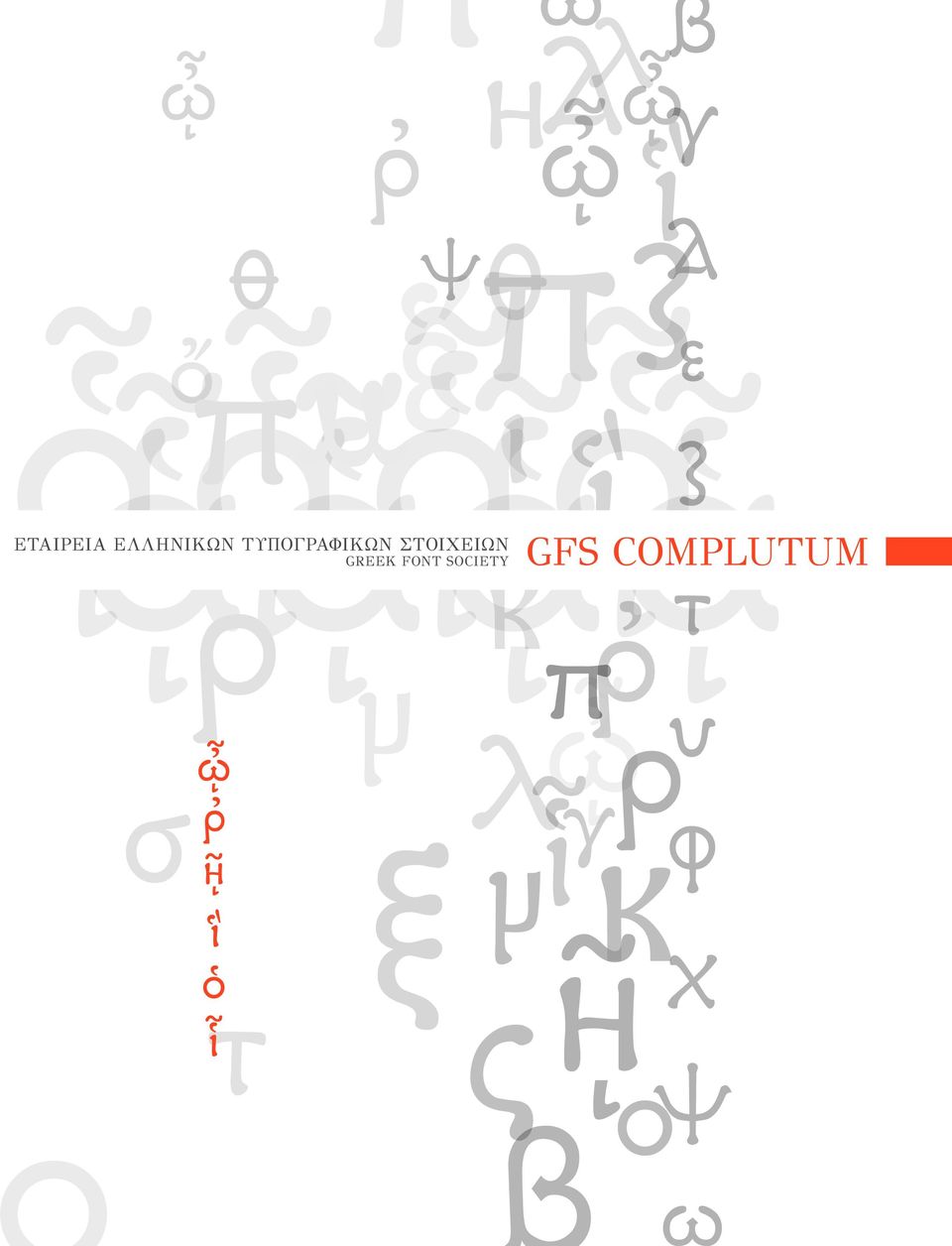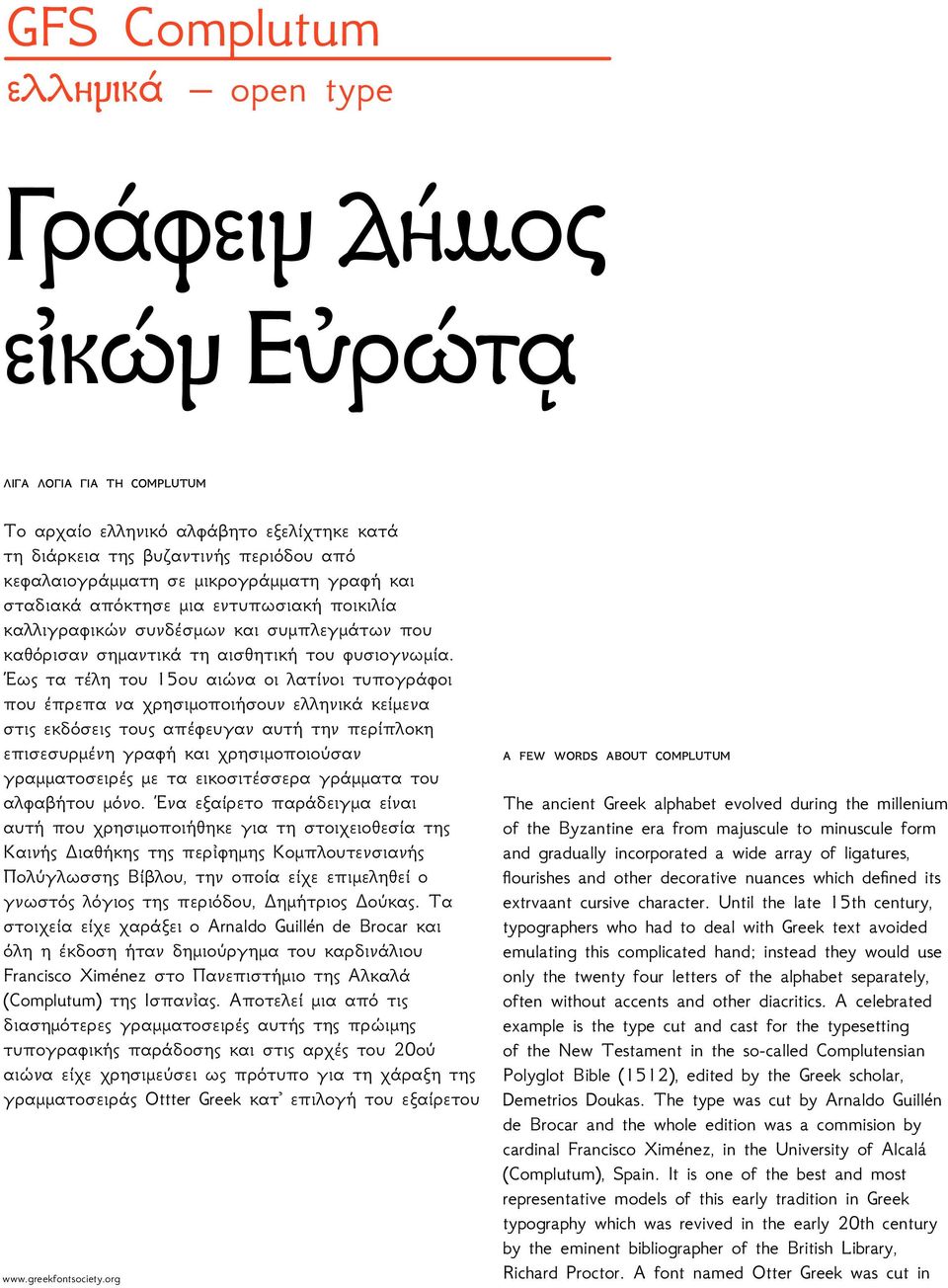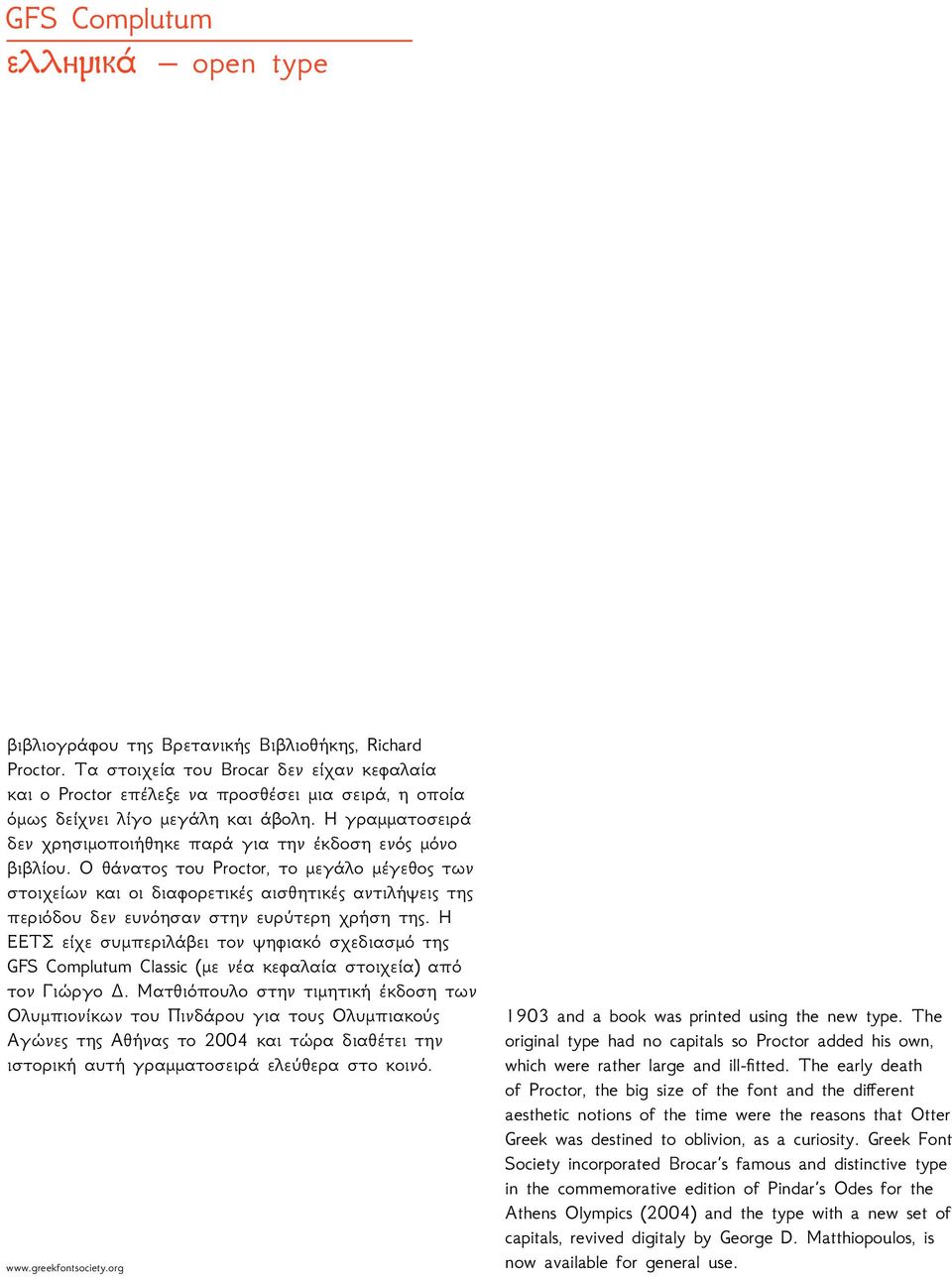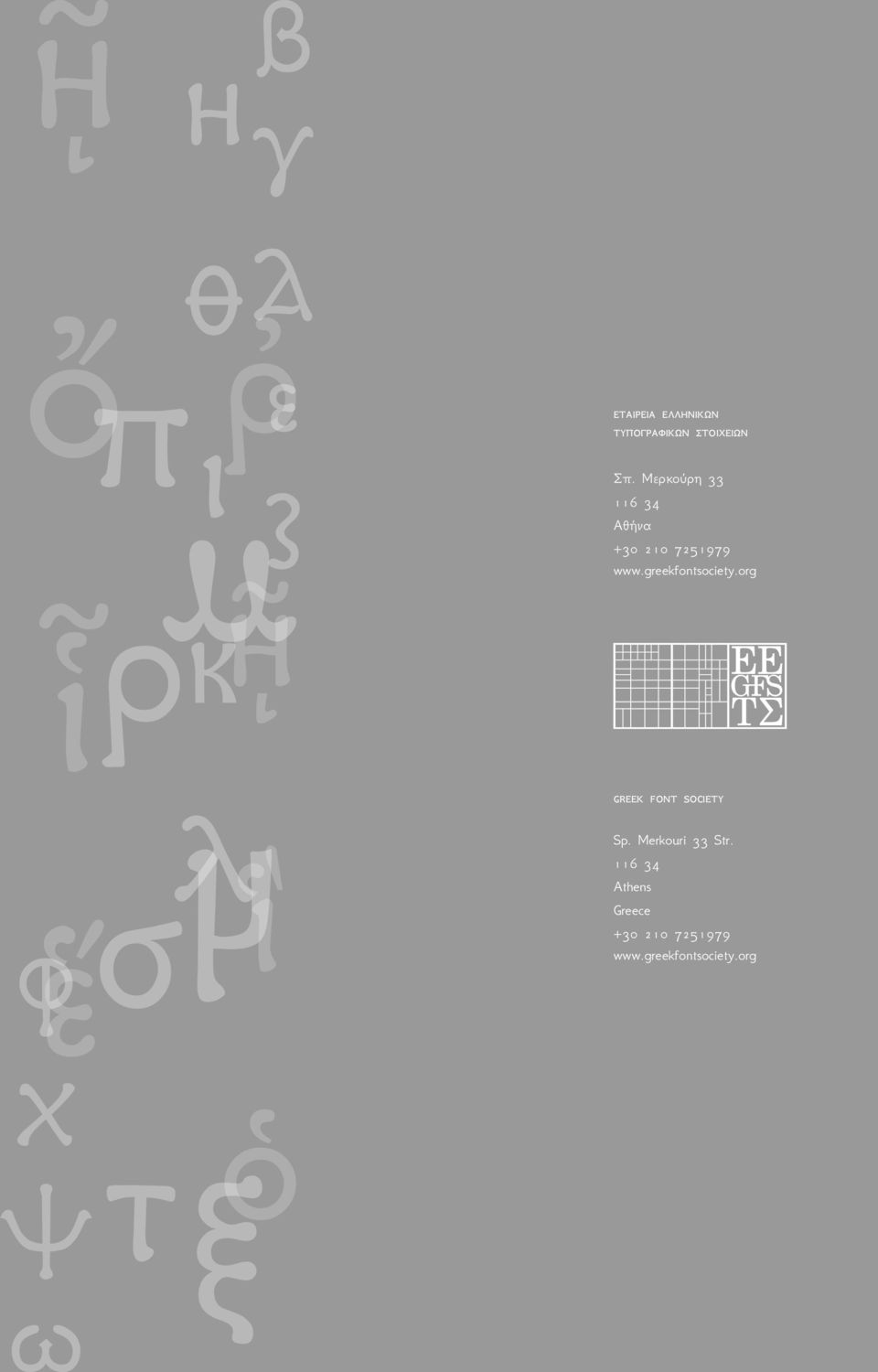
ΕΤΑΙΡΕΙΑ ΕΛΛΗΝΙΚΩΝ ΤΥΠΟΓΡΑΦΙΚΩΝ ΣΤΟΙΧΕΙΩΝ GREEK FONT SOCIETY GFS COMPLUTUM
1 ΕΤΑΙΡΕΙΑ ΕΛΛΗΝΙΚΩΝ ΤΥΠΟΓΡΑΦΙΚΩΝ ΣΤΟΙΧΕΙΩΝ GREEK FONT SOCIETY GFS COMPLUTUM
2 ελληνικά open type Γράφειν δήμος εἰκών Εὐρώτᾳ ΛΊΓΆ ΛΌΓΊΆ ΓΊΆ ΤΉ COMPLUTUM Το αρχαίο ελληνικό αλφάβητο εξελίχτηκε κατά τη διάρκεια της βυζαντινής περιόδου από κεφαλαιογράμματη σε μικρογράμματη γραφή και σταδιακά απόκτησε μια εντυπωσιακή ποικιλία καλλιγραφικών συνδέσμων και συμπλεγμάτων που καθόρισαν σημαντικά τη αισθητική του φυσιογνωμία. Έως τα τέλη του 15ου αιώνα οι λατίνοι τυπογράφοι που έπρεπα να χρησιμοποιήσουν ελληνικά κείμενα στις εκδόσεις τους απέφευγαν αυτή την περίπλοκη επισεσυρμένη γραφή και χρησιμοποιούσαν γραμματοσειρές με τα εικοσιτέσσερα γράμματα του αλφαβήτου μόνο. Ένα εξαίρετο παράδειγμα είναι αυτή που χρησιμοποιήθηκε για τη στοιχειοθεσία της Καινής Διαθήκης της περἰφημης Κομπλουτενσιανής Πολύγλωσσης Βίβλου, την οποία είχε επιμεληθεί ο γνωστός λόγιος της περιόδου, Δημήτριος Δούκας. Τα στοιχεία είχε χαράξει ο Arnaldo Guillén de Brocar και όλη η έκδοση ήταν δημιούργημα του καρδινάλιου Francisco Ximénez στο Πανεπιστήμιο της Αλκαλά (Complutum) της Ισπανἰας. Αποτελεί μια από τις διασημότερες γραμματοσειρές αυτής της πρώιμης τυπογραφικής παράδοσης και στις αρχές του 20ού αιώνα είχε χρησιμεύσει ως πρότυπο για τη χάραξη της γραμματοσειράς Ottter Greek κατ επιλογή του εξαίρετου A FEW WORDS ABOUT COMPLUTUM The ancient Greek alphabet evolved during the millenium of the Byzantine era from majuscule to minuscule form and gradually incorporated a wide array of ligatures, flourishes and other decorative nuances which defined its extrvaant cursive character. Until the late 15th century, typographers who had to deal with Greek text avoided emulating this complicated hand; instead they would use only the twenty four letters of the alphabet separately, often without accents and other diacritics. A celebrated example is the type cut and cast for the typesetting of the New Testament in the so-called Complutensian Polyglot Bible (1512), edited by the Greek scholar, Demetrios Doukas. The type was cut by Arnaldo Guillén de Brocar and the whole edition was a commision by cardinal Francisco Ximénez, in the University of Alcalá (Complutum), Spain. It is one of the best and most representative models of this early tradition in Greek typography which was revived in the early 20th century by the eminent bibliographer of the British Library, Richard Proctor. A font named Otter Greek was cut in
3 ελληνικά open type βιβλιογράφου της Βρετανικής Βιβλιοθήκης, Richard Proctor. Τα στοιχεία του Brocar δεν είχαν κεφαλαία και ο Proctor επέλεξε να προσθέσει μια σειρά, η οποία όμως δείχνει λίγο μεγάλη και άβολη. Η γραμματοσειρά δεν χρησιμοποιήθηκε παρά για την έκδοση ενός μόνο βιβλίου. Ο θάνατος του Proctor, το μεγάλο μέγεθος των στοιχείων και οι διαφορετικές αισθητικές αντιλήψεις της περιόδου δεν ευνόησαν στην ευρύτερη χρήση της. Η ΕΕΤΣ είχε συμπεριλάβει τον ψηφιακό σχεδιασμό της GFS Complutum Classic (με νέα κεφαλαία στοιχεία) από τον Γιώργο Δ. Ματθιόπουλο στην τιμητική έκδοση των Ολυμπιονίκων του Πινδάρου για τους Ολυμπιακούς Αγώνες της Αθήνας το 2004 και τώρα διαθέτει την ιστορική αυτή γραμματοσειρά ελεύθερα στο κοινό and a book was printed using the new type. The original type had no capitals so Proctor added his own, which were rather large and ill-fitted. The early death of Proctor, the big size of the font and the different aesthetic notions of the time were the reasons that Otter Greek was destined to oblivion, as a curiosity. Greek Font Society incorporated Brocar s famous and distinctive type in the commemorative edition of Pindar s Odes for the Athens Olympics (2004) and the type with a new set of capitals, revived digitaly by George D. Matthiopoulos, is now available for general use.
4 πόλύτόνίκό POLYTONIC πόλύτόνίκό ΣΎΝΌΛΌ ΧΆρΆΚΤΉρΏΝ ΑΒΓ ΕΖΗΘΙΚΛΜΝΞΟΠΡΣΤΥΦΧΨΩ ΆΈΉΊΪΌΎ ΫΏ ΆἉἍἋἏᾸᾺᾼᾉᾍᾋ ᾏᾈᾌᾊᾎ ἈἌἊἎᾹ ΈἙἝἛῈἘἜἚ ΉἩἭἫἯῊῌᾙᾝᾛᾟᾘᾜ ᾚᾞἨἬἪἮ ΊἹἽἻἿῘῚἸἼἺἾῙ ΌὉὍὋῸὈὌὊῬ ΎὙὝὛὟῨῪῩ ΏὩὭὫὯῺῼᾩᾭᾫᾯᾨᾬ ᾪᾮὨὬὪὮ αβγδεζηθικλμνξοπρστυφχψως άέήίϊ ΐόύΰϋώ ὰάἀἁἂἃἄἅἆἇᾀᾁᾂᾃᾄᾅᾆᾇᾰᾱᾲᾳᾴᾶᾷ ὲέἐἑἒ ἓ ἔἕ ὴήᾐᾑᾒᾓᾔᾕᾖᾗῂῃῄῆῇἠἡἢἣἤἥἦἧ ὶί ῐ ῑ ῒ ΐ ῖ ῗἰἱ ἲ ἳ ἴ ἵ ἶἷ ὸόὀὁὂὃὄὅῤῥ ὺύὐὑὒὓὔὕὖὗῠῡῢΰῦῧ ὼώὠὡὢὣὤὥὦὧᾠᾡᾢᾣᾤᾥᾦᾧῲῳῴῶῷ
5 SAMPLE TEXTS COMPLUTUM ΛΈΎΚΆ 6 ΣΤΊΓµΈΣ Η ΣΥΝΑΝΤΗΣΗ των πνευματικών και καλλιτεχνικών παραδόσεων της Ελληνικής Ανατολής και της ευρωπαϊκής Δύσης στην Κρήτη την εποχή της Βενετοκρατίας οδήγησε σε διάφορες ζυμώσεις και δημιούργησε το κατάλληλο κλίμα για την ανάπτυξη και καρποφορία στο νησί ενός πολιτισμού με πολλές εκφάνσεις και ιδιαίτερες αποχρώσεις. Στην τελευταία ιδίως περίοδο της Βενετοκρατίας στην οικονομική ευημερία των κρητικών πόλεων της πρωτεύουσας. COMPLUTUM ΛΈΎΚΆ 7 ΣΤΊΓµΈΣ Η ΣΥΝΑΝΤΗΣΗ των πνευματικών και καλλιτεχνικών παραδόσεων της Ελληνικής Ανατολής και της ευρωπαϊκής Δύσης στην Κρήτη την εποχή της Βενετοκρατίας οδήγησε σε διάφορες ζυμώσεις και δημιούργησε το κατάλληλο κλίμα για την ανάπτυξη και καρποφορία στο νησί ενός πολιτισμού με πολλές εκφάνσεις και ιδιαίτερες αποχρώσεις. COMPLUTUM ΛΈΎΚΆ 8 ΣΤΊΓµΈΣ Η ΣΥΝΑΝΤΗΣΗ των πνευματικών και καλλιτεχνικών παραδόσεων της Ελληνικής Ανατολής και της ευρωπαϊκής Δύσης στην Κρήτη την εποχή της Βενετοκρατίας οδήγησε σε διάφορες ζυμώσεις και δημιούργησε το κατάλληλο κλίμα για την ανάπτυξη και καρποφορία στο νησί ενός πολιτισμού με COMPLUTUM ΛΈΎΚΆ 9 ΣΤΊΓµΈΣ Η ΣΥΝΑΝΤΗΣΗ των πνευματικών και καλλιτεχνικών παραδόσεων της Ελληνικής Ανατολής και της ευρωπαϊκής Δύσης στην Κρήτη την εποχή της Βενετοκρατίας οδήγησε σε διάφορες ζυμώσεις και COMPLUTUM ΛΈΎΚΆ 10 ΣΤΊΓµΈΣ Η ΣΥΝΑΝΤΗΣΗ των πνευματικών και καλλιτεχνικών παραδόσεων της Ελληνικής Ανατολής και της ευρωπαϊκής Δύσης στην Κρήτη την εποχή της Βενετοκρατίας οδήγησε σε COMPLUTUM ΛΈΎΚΆ 12 ΣΤΊΓµΈΣ Η ΣΥΝΑΝΤΗΣΗ των πνευματικών και καλλιτεχνικών παραδόσεων της Ελληνικής Ανατολής COMPLUTUM ΛΈΎΚΆ 14 ΣΤΊΓµΈΣ Η ΣΥΝΑΝΤΗΣΗ των πνευματικών και καλλιτεχνικών παραδόσεων της Ελληνικής SAMPLE TEXT 12 PT GFS COMPLUTUM Η συνάντηση των πνευματικών και καλλιτεχνικών παραδόσεων της Ελληνικής Ανατολής και της ευρωπαϊκής Δύσης στην Κρήτη την εποχή της Βενετοκρατίας οδήγησε σε διάφορες ζυμώσεις και δημιούργησε το κατάλληλο κλίμα για την ανάπτυξη και καρποφορία στο νησί ενός πολιτισμού με πολλές εκφάνσεις και ιδιαίτερες αποχρώσεις. Στην τελευταία ιδίως περίοδο της Βενετοκρατίας στην οικονομική ευημερία των κρητικών πόλεων της πρωτεύουσας. Η συνάντηση των πνευματικών και καλλιτεχνικών παραδόσεων της Ελληνικής Ανατολής και της ευρωπαϊκής Δύσης στην Κρήτη την εποχή της Βενετοκρατίας οδήγησε σε διάφορες ζυμώσεις και δημιούργησε το κατάλληλο κλίμα για την αγάπη και καρποφορία στο νησί ενός πολιτισμού με πολλές εκφάνσεις και ιδιαίτερες αποχρώσεις. Στην τελευταία ιδίως περίοδο της Βενετοκρατίας στην οικονομική ευημερία των κρητικών πόλεων της πρωτεύουσας.
6 ΈΊΓµΆ πόλύτόνίκόύ ΚΈΊµΈΝΌΎ ΤΑ ΠΑΛΑΙΑ ΤΩΝ ΛΑΚΕΔΑΙΜΟΝΙΩΝ ΕΠΙΤΗΔΕΥΜΑΤΑ Τῶν εἰσιόντων εἰς τὰ συσσίτια ἑκάστῳ δεικνύων ὁ πρεσβύτατος τὰς θύρας, «διὰ τούτων» φησίν, «οὐδεὶς ἐξέρχεται λόγος». Δοκιμαζομένου μάλιστα παρ αὐτοῖς τοῦ μέλανος λεγομένου ζωμοῦ, ὥστε μὴ κρεαδίου δεῖσθαι τοὺς πρεσβυτέρους, παραχωρεῖν δὲ τοῖς νεανίσκοις, λέγεται Διονύσιος ὁ τῆς Σικελίας τύραννος τούτου χάριν Λακωνικὸν μάγειρον πρίασθαι καὶ προστάξαι σκευάσαι αὐτῷ μηδενὸς φειδόμενον ἀναλώματος ἔπειτα γευσάμενον καὶ δυσχεράναντα ἀποπτύσαι καὶ τὸν μάγειρον εἰπεῖν, «ὦ βασιλεῦ, τοῦτον δεῖ τὸν ζωμὸν γυμνασάμενον Λακωνικῶς καὶ τῷ Εὐρώτᾳ λελουμένον ἐποψᾶσθαι». Πιόντες οἱ Λάκωνες ἐν τοῖς συσσιτίοις μετρίως ἀπίασι δίχα λαμπάδος οὐ γὰρ ἔξεστι πρὸς φῶς βαδίζειν οὔτε ταύτην οὔτε ἄλλην ὁδόν, ὅπως ἐθίζωνται σκότους καὶ νυκτὸς εὐθαρσῶς καὶ ἀδεῶς ὁδεύειν. Γράμματα ἕνεκα τῆς χρείας ἐμάνθανον τῶν δὲ ἄλλων παιδευμάτων ξενηλασίαν ἐποιοῦντο, οὐ μᾶλλον ἀνθρώπων ἢ λόγων. ἡ δὲ παιδεία ἦν αὐτοῖς πρὸς τὸ ἄρχεσθαι καλῶς καὶ καρτερεῖν πονοῦντα καὶ μαχόμενον νικᾶν ἢ ἀποθνῄσκειν. Διετέλουν δὲ καὶ ἄνευ χιτῶνος, ἓν ἱμάτιον εἰς τὸν ἐνιαυτὸν λαμβάνοντες, αὐχμηροὶ τὰ σώματα καὶ λουτρῶν καὶ ἀλειμμάτων κατὰ τὸ πλεῖστον ἀπεχόμενοι. Ἐκάθευδον δὲ οἱ νέοι ὁμοῦ κατ ἴλην καὶ κατὰ ἀγέλην ἐπὶ στιβάδων, ἃς αὐτοὶ συνεφόρουν, τοῦ παρὰ τῷ Εὐρώτᾳ πεφυκότος καλάμου τὰ ἄκρα ταῖς χερσὶν ἄνευ σιδήρου κατακλάσαντες ἐν δὲ τῷ χειμῶνι τοὺς λεγομένους λυκόφονας ὑπεβάλλοντο καὶ κατεμείγνυσαν ταῖς στιβάσι, θερμαντικὸν ἔχειν τι τῆς ὕλης δοκούσης. Ἐρᾶν τῶν τὴν ψυχὴν σπουδαίων παίδων ἐφεῖτο τὸ δὲ πλησιάζειν αἰσχρὸν νενόμιστο, ὡς τοῦ σώματος ἐρῶντας ἀλλ οὐ τῆς ψυχῆς ὁ δὲ ἐγκληθεὶς ὡς ἐπ αἰσχύνῃ πλησιάζων ἄτιμος διὰ βίου ἦν. Ἔθος ἦν καὶ τοὺς νεωτέρους ὑπὸ τῶν πρεσβυτέρων ἐρωτᾶσθαι ποῦ πορεύονται καὶ